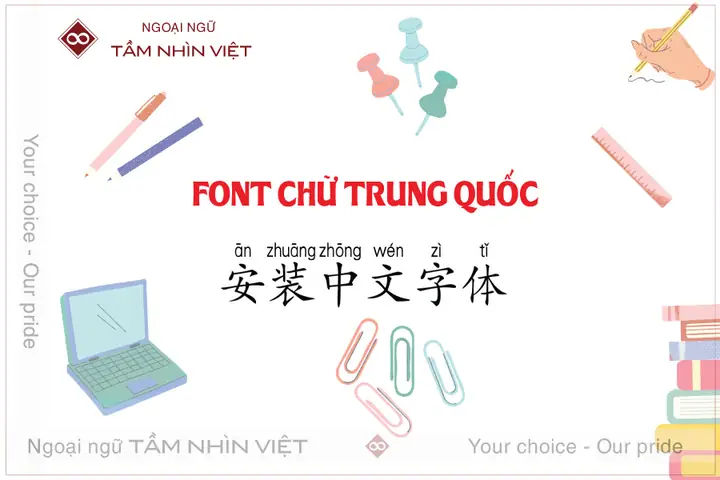
Bạn đang tìm kiếm cách cài đặt font tiếng Trung có pinyin để hỗ trợ việc học, dịch thuật hoặc thiết kế? Việc có một bộ font chất lượng với đầy đủ ký tự Hán tự và pinyin đi kèm là điều cần thiết để đảm bảo văn bản hiển thị chính xác, đẹp mắt và dễ đọc. summerland hiểu rõ nhu cầu này và đã tổng hợp một hướng dẫn chi tiết, giúp bạn tải về và cài đặt bộ font tiếng Trung có pinyin một cách nhanh chóng, đơn giản và hoàn toàn miễn phí.
Font tiếng Trung có Pinyin là gì và tại sao bạn cần?
Font tiếng Trung có pinyin là những bộ phông chữ được thiết kế đặc biệt để hiển thị đồng thời hai yếu tố: ký tự Hán tự (chữ Hán) và phiên âm pinyin (dùng chữ Latinh). Pinyin là hệ thống phiên âm chính thức của tiếng Trung Quốc, sử dụng bảng chữ cái La-tinh để biểu thị cách phát âm của từng chữ Hán. Việc có pinyin đi kèm giúp người học dễ dàng tra cứu, luyện phát âm và ghi nhớ mặt chữ.
Lợi ích khi sử dụng Font tiếng Trung có Pinyin
- Hỗ trợ học tiếng Trung: Đây là công cụ tuyệt vời cho người mới bắt đầu học tiếng Trung. Khi nhìn vào một văn bản, bạn có thể dễ dàng đối chiếu giữa chữ Hán và cách đọc của nó.
- Tăng tính thẩm mỹ cho tài liệu: Các bộ font hiện đại thường có thiết kế đẹp mắt, giúp tài liệu học tập, bài giảng, hoặc các ấn phẩm văn hóa trở nên chuyên nghiệp và dễ đọc hơn.
- Tiện lợi trong dịch thuật và biên tập: Đối với những người làm công việc dịch thuật, việc có sẵn pinyin sẽ giúp kiểm tra chính tả, phát âm và đảm bảo tính chính xác của bản dịch.
- Ứng dụng trong thiết kế đồ họa: Khi thiết kế các poster, banner, hay các sản phẩm liên quan đến văn hóa Trung Hoa, font có pinyin sẽ giúp truyền tải thông điệp một cách đầy đủ và sinh động hơn.
Tổng hợp các Font tiếng Trung có Pinyin phổ biến, chất lượng cao
Trên thị trường có rất nhiều loại font tiếng Trung có pinyin, mỗi loại lại có những đặc điểm riêng biệt về thiết kế, độ rõ nét và mức độ hỗ trợ ký tự. Dưới đây là danh sách các font phổ biến nhất mà summerland đã chọn lọc và kiểm tra kỹ lưỡng.
1. Font FZSongTi (Phượng Hoàng – Phổ thông)
Font FZSongTi là một trong những lựa chọn hàng đầu cho việc gõ chữ Hán trên máy tính. Font này có phong cách chữ in, nét chữ rõ ràng, dễ đọc, phù hợp với việc soạn thảo văn bản, viết bài luận, hay làm bài tập. Đặc biệt, phiên bản kèm pinyin của FZSongTi được đánh giá rất cao về độ chính xác và tính thẩm mỹ.
- Đặc điểm nổi bật:
- Phong cách chữ in truyền thống, rất phù hợp với văn bản học thuật.
- Ký tự Hán tự đầy đủ, bao gồm cả các ký tự thông dụng và ít dùng đến.
- Pinyin được thiết kế nhỏ gọn, nằm phía trên hoặc bên cạnh chữ Hán, không làm rối mắt người đọc.
- Phù hợp với: Người học tiếng Trung, sinh viên, giáo viên, người làm văn phòng cần soạn thảo tài liệu có chứa chữ Hán.
2. Font Hanyi(华文)- Truyền thống, uy nghi
Font Hanyi là một dòng font cổ điển, mang đậm phong cách thư pháp Trung Hoa. Font này thường được sử dụng trong các ấn phẩm mang tính chất văn hóa, nghệ thuật, hoặc trong các tài liệu cần thể hiện sự trang trọng. Font Hanyi có nhiều biến thể, trong đó phiên bản có pinyin là lựa chọn lý tưởng cho những ai muốn kết hợp giữa vẻ đẹp truyền thống và tính năng hiện đại.
- Đặc điểm nổi bật:
- Thiết kế mang đậm dấu ấn thư pháp, nét chữ uyển chuyển, mềm mại.
- Tạo cảm giác trang trọng, cổ điển cho văn bản.
- Pinyin được tích hợp một cách hài hòa, không làm mất đi vẻ đẹp tổng thể của font.
- Phù hợp với: Thiết kế poster, banner, logo, các ấn phẩm văn hóa, hoặc những ai yêu thích phong cách cổ điển Trung Hoa.
3. Font Microsoft YaHei (Vi Phá – Hiện đại)
Microsoft YaHei là font mặc định trên hệ điều hành Windows, được biết đến với sự hiện đại, sạch sẽ và dễ đọc trên màn hình. Font này rất phổ biến trong môi trường làm việc văn phòng và học tập. Phiên bản có pinyin của Microsoft YaHei giữ nguyên những ưu điểm vốn có, đồng thời bổ sung thêm tính năng hỗ trợ học tập, khiến nó trở thành một lựa chọn lý tưởng cho người dùng phổ thông.